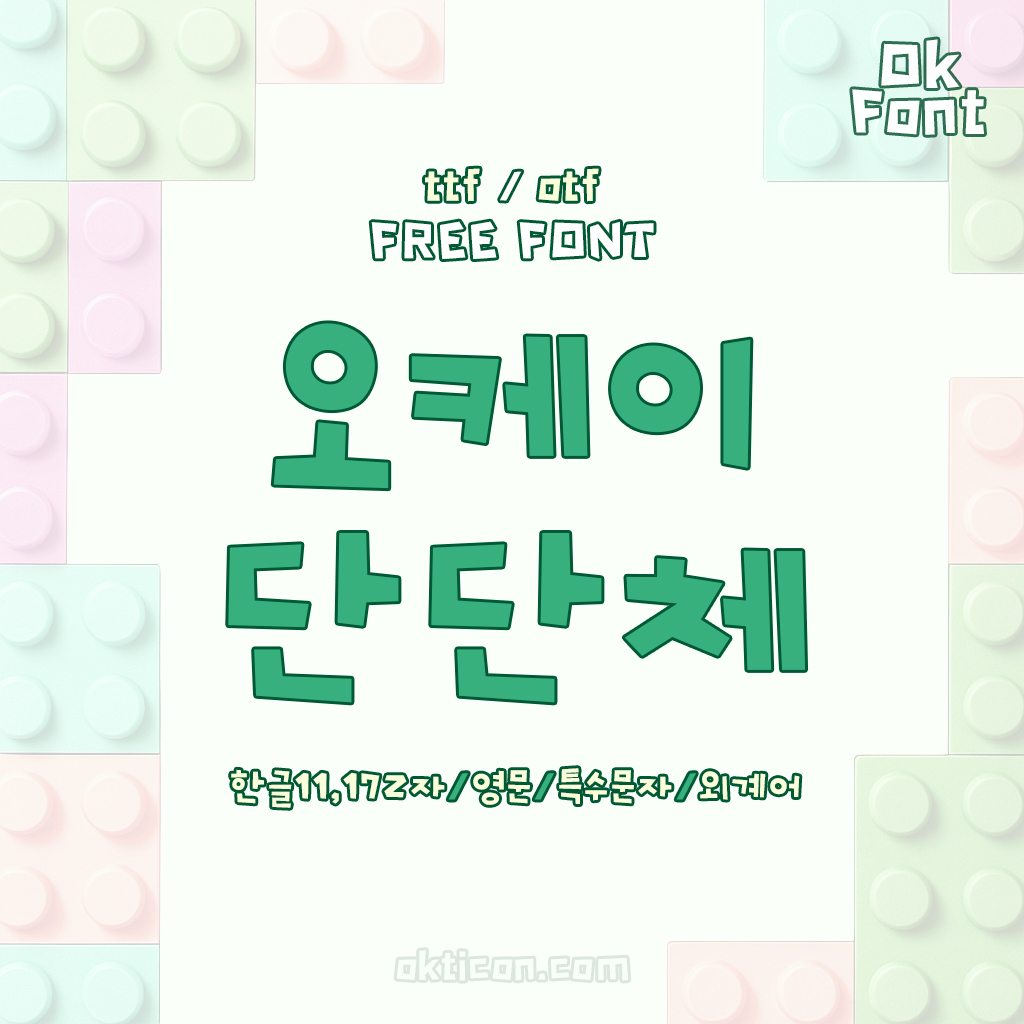
OK단단체 — 오케이콘에서 배포하는 무료 폰트입니다. 삐뚤빼뚤한 글자와 통통한 획이 어우러진 귀엽고 개성 있는 장식 손글씨체
오케이티콘이 2025년에 배포한 제목용 서체입니다. 이름의 Ok 때문에 금융 회사를 떠올리기 쉬운데, OK금융그룹과는 관계가 없습니다. 오케이티콘이라는 개인 제작자가 만든 폰트입니다.
제작 방식이 특이합니다. 제작자는 폰트 업체에 맡기지 않고 독학으로 만들었다고 밝혔고, 이름의 단단에 대해서는 제목용으로 딱 맞는 두툼하고 시원한 폰트라고 설명했습니다.
파일에서 재어 보면 받침이 붙을 때 글자 높이가 달라지는 탈네모틀이라 손글씨의 흔들림이 남아 있고, 낱자는 가로로 퍼져 있습니다. 현대 한글 11,172자를 모두 담았습니다. 라이선스가 이 목록에서 가장 넉넉한 축입니다. 인쇄와 웹, 영상, 임베딩, BI와 CI에 쓸 수 있고 색상이나 자간, 굵기를 조정하는 수정도 허용됩니다. 다만 폰트 파일을 팔거나 직접 올려 재배포하는 것은 금지되고 인공지능 학습에 쓰는 것도 금지됩니다.